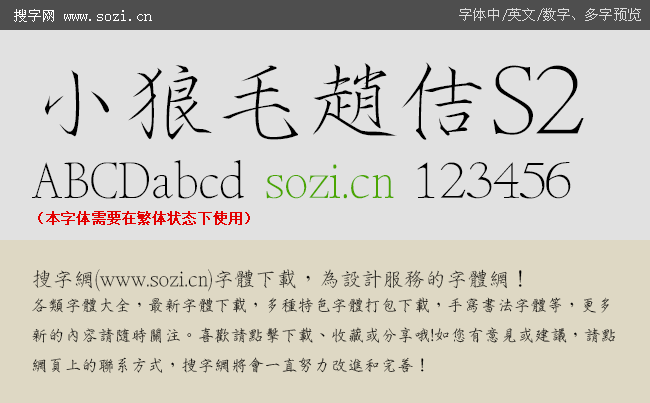
小狼毛趙佶S2
搜字網(wǎng)提供一款書法字體小狼毛趙佶S2字體下載,瘦金體為宋徽宗趙佶所創(chuàng),是書法史上的一項(xiàng)獨(dú)創(chuàng)。瘦金體運(yùn)筆飄忽快捷,筆跡瘦勁,至瘦而不失其肉,轉(zhuǎn)折處可明顯見到藏鋒,露鋒等運(yùn)轉(zhuǎn)提頓痕跡,是一種風(fēng)格相當(dāng)獨(dú)特的字體。適合字貼、招貼、書法畫冊(cè)設(shè)計(jì)應(yīng)用。